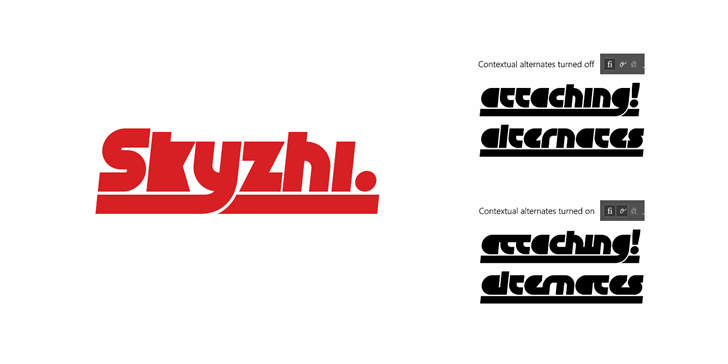
Skyzhi Font
Aqui está uma descrição para a página de download da fonte ‘Skyzhi Font’ na categoria Retro Fonts: Em um mundo onde o digital domina, uma fonte vintage, chamada Skyzhi, oferece um mergulho no passado tecnológico. Desenvolvida pelo designer Hamilton, essa fonte retro traz consigo a essência do design de computador dos anos 80 e 90, criando uma paleta vibrante que combina com os desafios modernos da atualidade. Com um design minimalista e elegante, Skyzhi é perfeita para aplicativos digitais retro ou interfaces gráficas vintage. Seja você um designer de software, desenvolvedor web ou simplesmente alguém que gosta de uma fonte do tempo dos computadores pessoais, essa fonte retro oferece o acabamento perfeito para qualquer projeto. Visite o site oficial e adquira sua licença comercial agora mesmo. Skyzhi é a combinação perfeita entre funcionalidade e estilo, ideal para dar um toque diferenciado aos seus designs digitais. Com uma paleta de cores vibrantes e linhas sutis, você pode criar interfaces gráficas memoráveis que cativam o seu público-alvo. E não é apenas sua fonte que ficará impressa na memória – os usuários também lembrarão a beleza do design retro dessa fonte única.